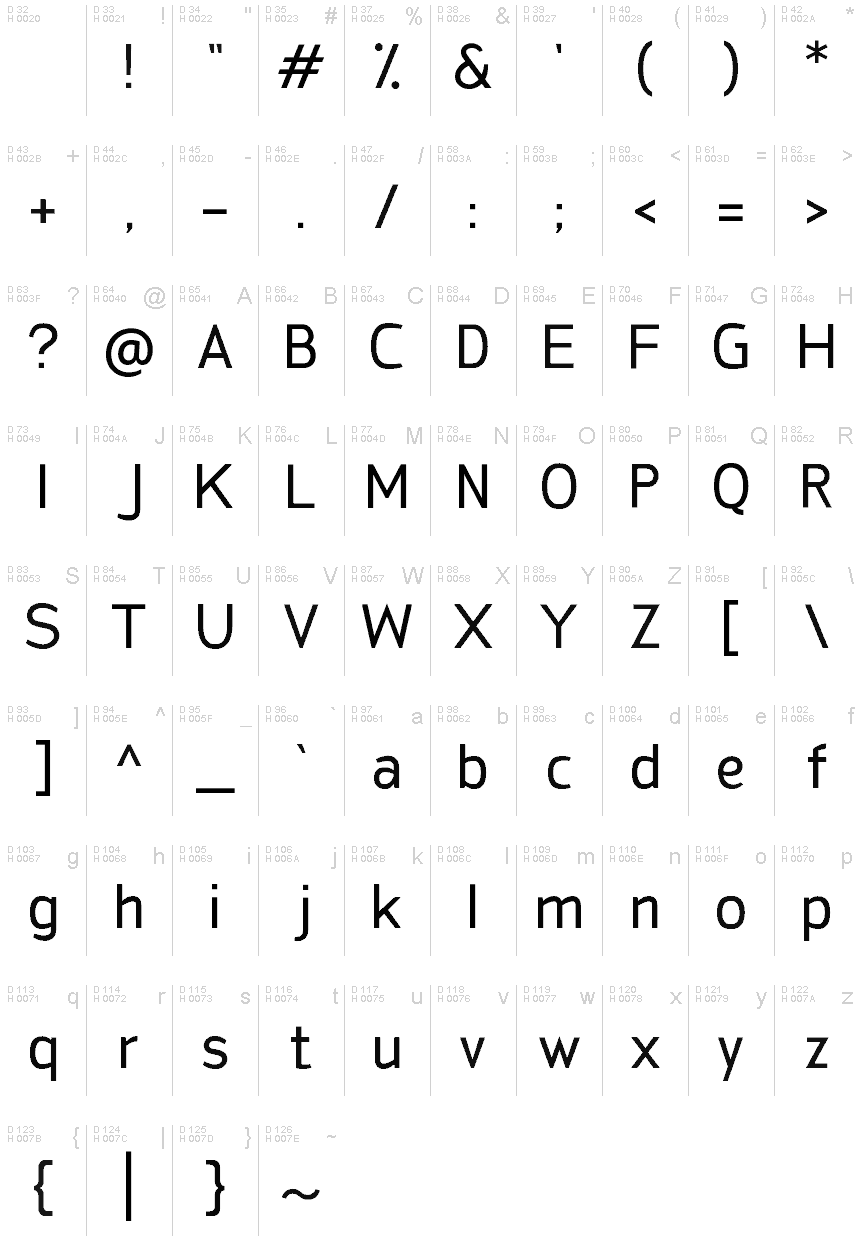
San Frediano to geometryczny krój bezszeryfowy, inspirowany słynną dzielnicą Florencji, w której mieści się Studio Monocromo.
San Frediano kryje w swoich kształtach wiele drobnych detali, które stają się widoczne w dużych rozmiarach – zupełnie jak uliczki tej dzielnicy, które za każdym zakrętem skrywają niespodzianki.
Proporcje wysokości między wielkimi a małymi literami sprawiają, że jest to doskonały font webowy, sprawdzający się zarówno w składzie tekstu, jak i w ekspozycji. Znajdzie zastosowanie w nagłówkach gazet, tekstach głównych, reklamach, identyfikacji wizualnej i wielu innych projektach.